今回のバンドルは「大人気!ユニバーサルデザインフォント集」。子供からお年寄りまで読みやすいユニバーサルデザインの丸ゴシック&角ゴシック各10書体と、Webフォントバージョンも収録。このバンドルさえあれば印刷にもウェブにも対応できます。
「大人気!ユニバーサルデザインフォント集」の気になる中身
AFSまるご風10書体セット
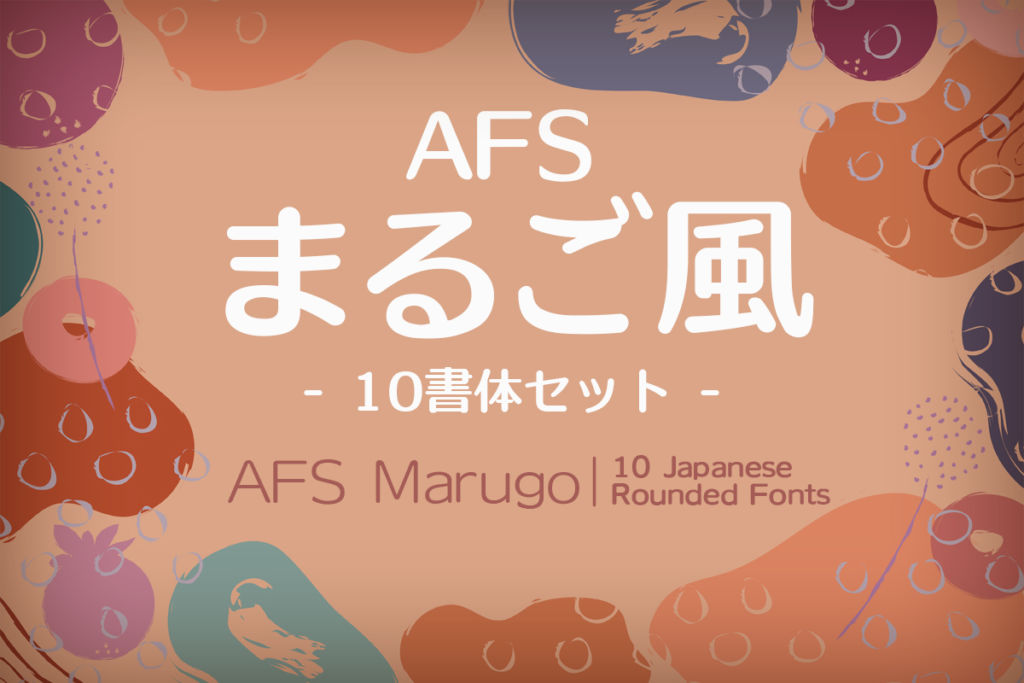
幅広く受け入れられるやさしい雰囲気が魅力の「AFSまるご風10書体セット」。ウェイトも豊富で、用途に応じて細かく使い分けられます。
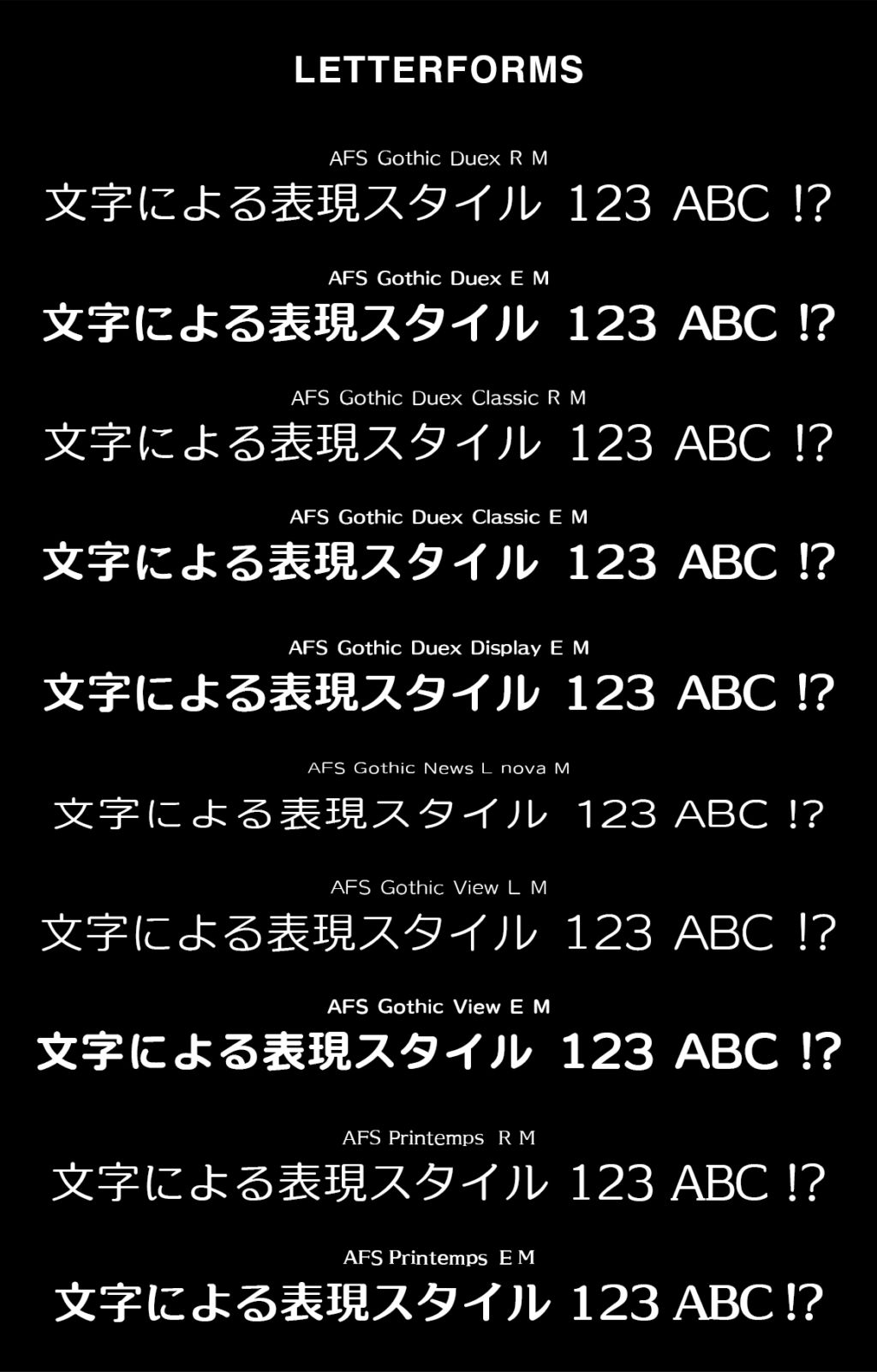
- AFS GothicDuex Classic E_M
- AFS GothicDuex Classic R_M
- AFS GothicDuex Display E_M
- AFS GothicDuex E_M
- AFS GothicDuex R_M
- AFS GothicNews Lnova_M
- AFS GothicView E_M
- AFS GothicView L_M
- AFS Printemps E_M
- AFS Printemps R_M